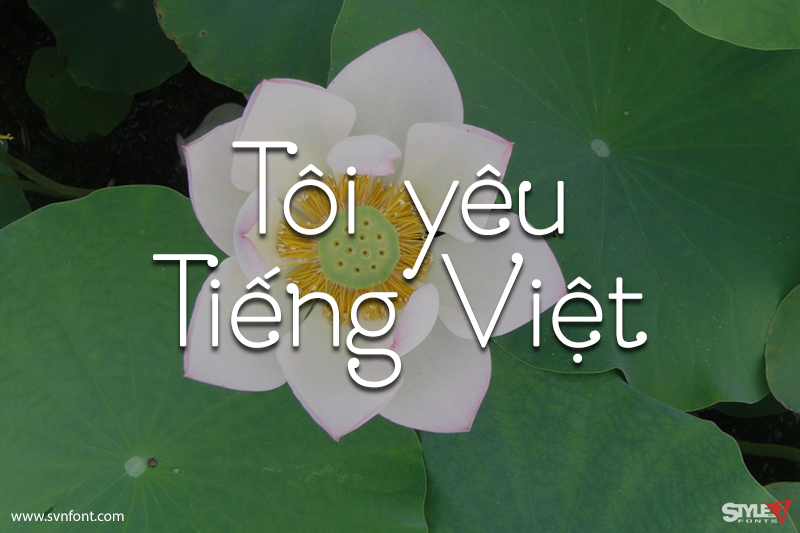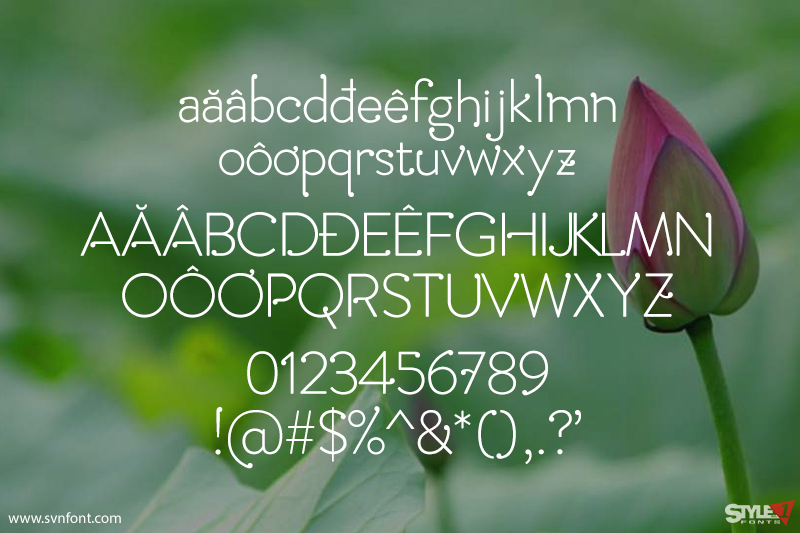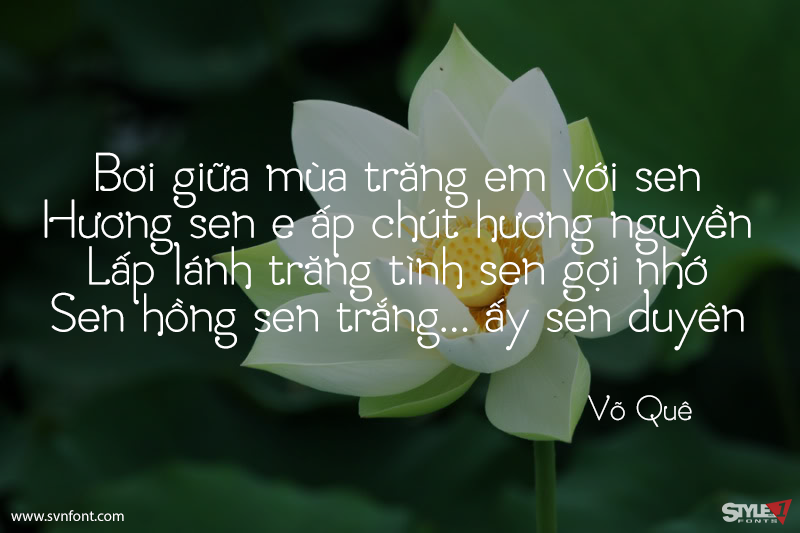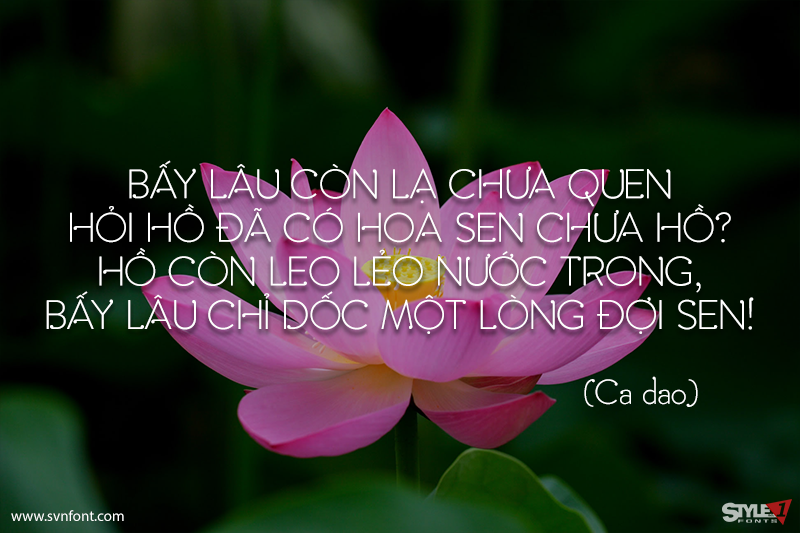
Amsdam là một font thú vị mang phong cách thanh lịch, phù hợp nhất cho tiêu đề và các thiết kế đồ họa.
Nhà thiết kế: Davide Mancini
Amsdam là một font thú vị mang phong cách thanh lịch, phù hợp nhất cho tiêu đề và các thiết kế đồ họa.
Nhà thiết kế: Davide Mancini